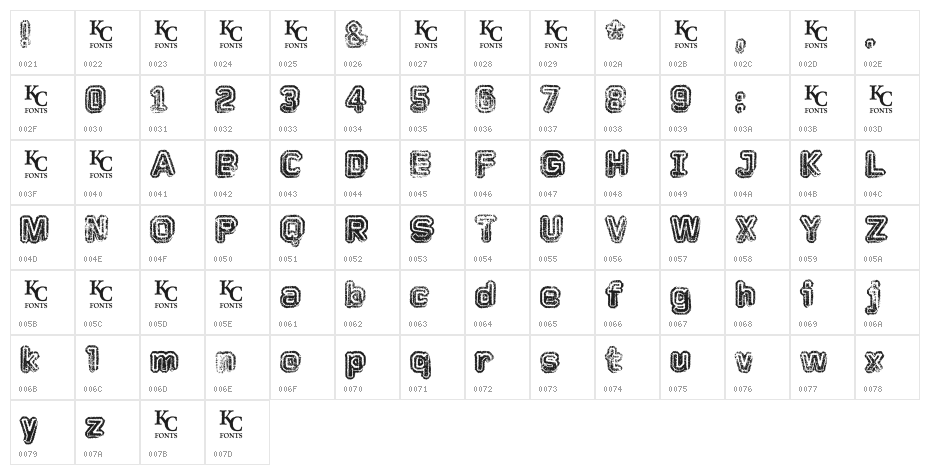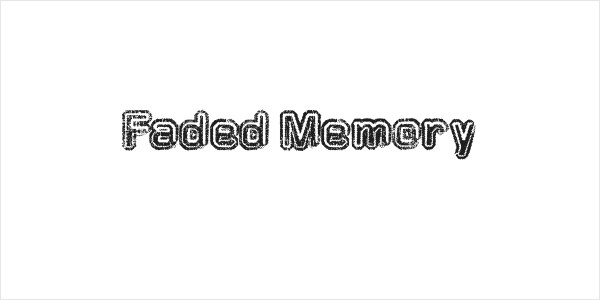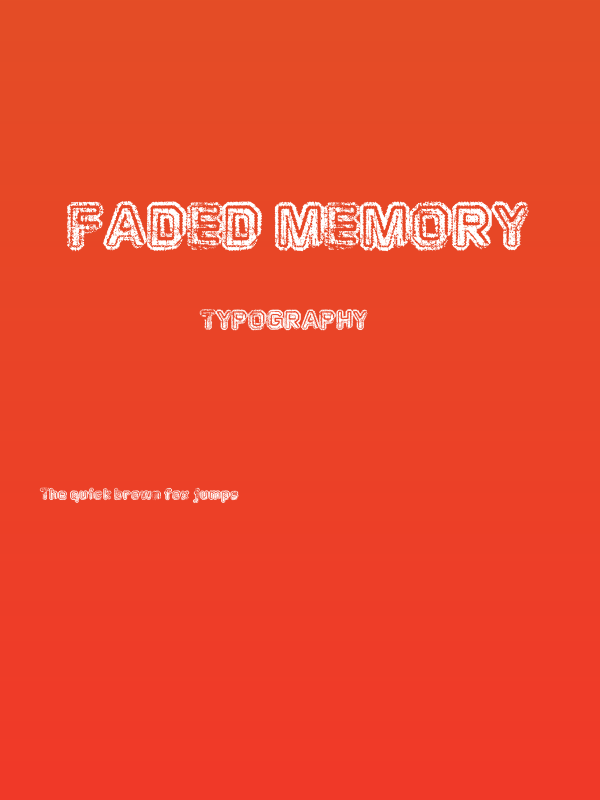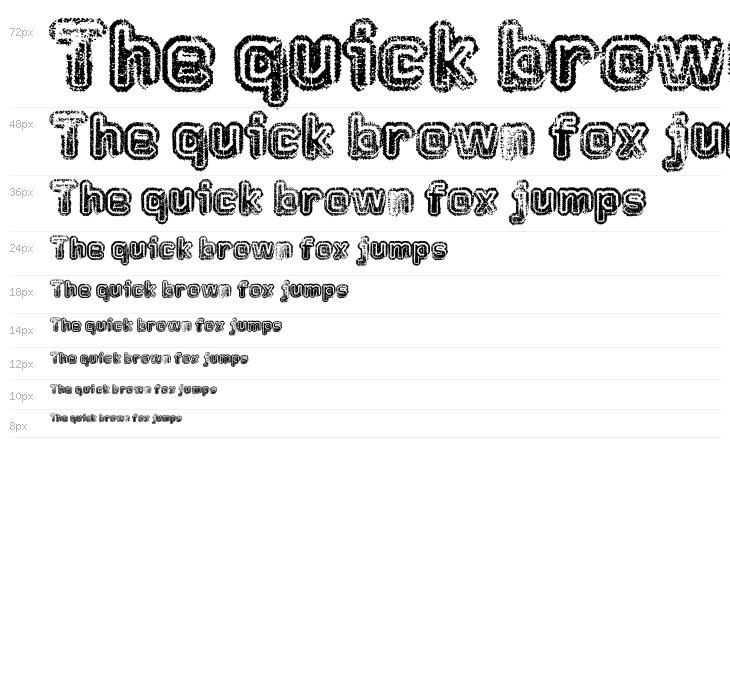
Faded Memory Font
✎ Distorted Eroded
| Progetti proposti | Ideal for projects that require a vintage or retro aesthetic, such as posters, album covers, and branding for rustic or artisanal products. |